邀请函用什么字体?11款适合制作邀请函的字体推荐
本文给大家分享11款适合做邀请函的字体,希望对你在后面的邀请函制作的时候有所帮助。
婚礼邀请函
字由芳华体
字由芳华体是一款温柔的手写风格的字体,笔画柔和。不是那种特别正式的手写体,带着一点随性和温度。适合做请柬的主标题,特别是文艺风的邀请函。
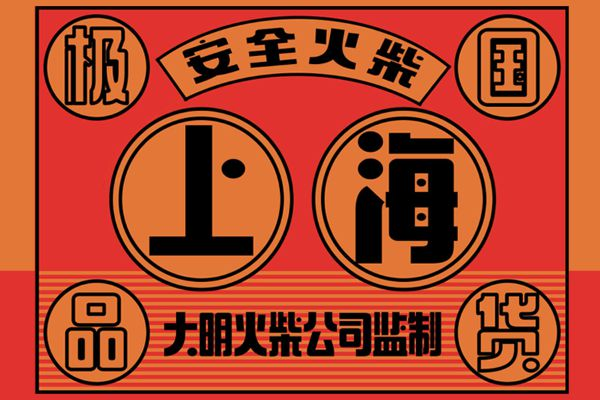
点字明刻本婉宋
点字明刻本婉宋是一款带有宋体韵味的字体,但比传统宋体多了一份婉约和柔和。适合传统风格的邀请函,尤其是中式婚礼、传统节日活动等。既有宋体的优雅,又不失温婉的气质。
江西拙楷
江西拙楷是一款带着朴拙手工感的楷书。和传统的楷书不太一样,它不是那种规规矩矩的写法,而是保留了手写的质朴感。适合中式婚礼请柬,或者带有传统文化元素的活动邀请。用在“囍”字、新人姓名和古风邀请语上,东方韵味很足。
字由锦绣
字由锦绣是一款中国风手写体,设计理念是“繁花如锦,神采挥洒”。方头起笔利落干脆,传递出力量感。适合国风主题的邀请函,比如中式婚礼、汉服活动、传统文化类聚会。兼具力量感与手写温度,用在标题上很有冲击力。
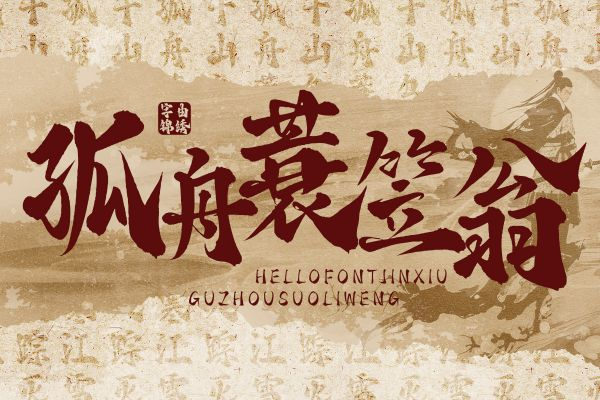
商务活动邀请函
字由文艺黑是一款现代简约风格字体,字形方正饱满,重心居中。保留了黑体的稳重感,但又加入了艺术弧线的设计,不会显得太死板。适合做邀请函的主标题或者新人名字的排版。不管是婚礼邀请还是活动邀请,用这个字体做标题都很提气。
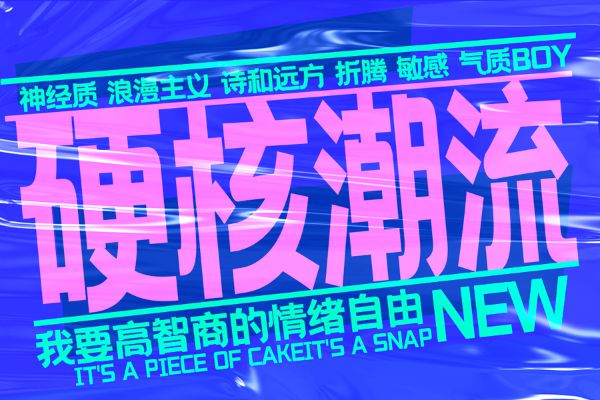
字由长宋
字由长宋传统宋体的装饰性元素做了简化和几何化处理。瘦长的结构,冷静清晰。适合简约、精致、当代感的邀请函。我做过一次设计展的邀请,用这个字体做正文排版,干净利落,阅读体验很好。
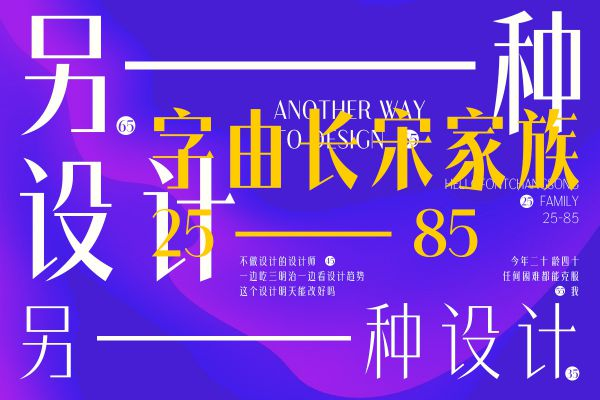
思源宋体
谷歌与Adobe联合打造的开源现代宋体,端庄优雅。字形方正稳重,保留了宋体的传统韵味,又融入了现代设计感。如果邀请函信息比较多,用思源宋体做正文,清晰又体面。
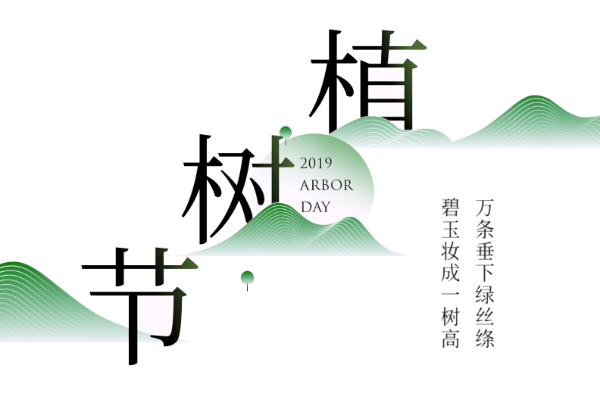
优设标题黑
优设标题黑方正有力,笔画粗重有设计感。属于展示类黑体,视觉冲击力强。适合做时间、地点的标注,或者邀请函中需要突出的关键信息。我经常用它来标日期和场地,粗重有力,一眼就能看到。
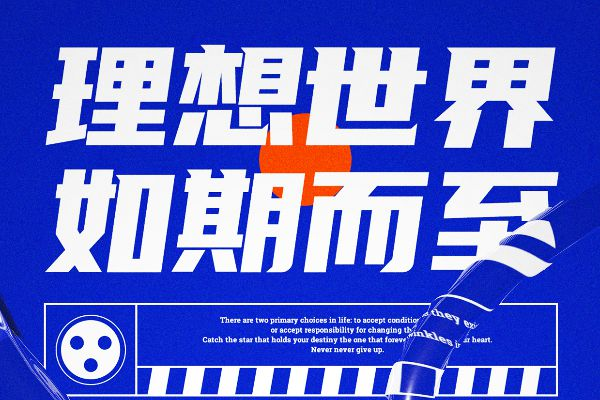
文艺/创意活动邀请函
剑豪体
剑豪体是Aa字库推出的中国风手写体。中宫收紧,结构紧凑中透出张力。笔型融入利落斜切,有剑势般的刚劲。适合武侠风、古风类的邀请函。江湖气息很浓,用在武侠主题的活动上特别对味。
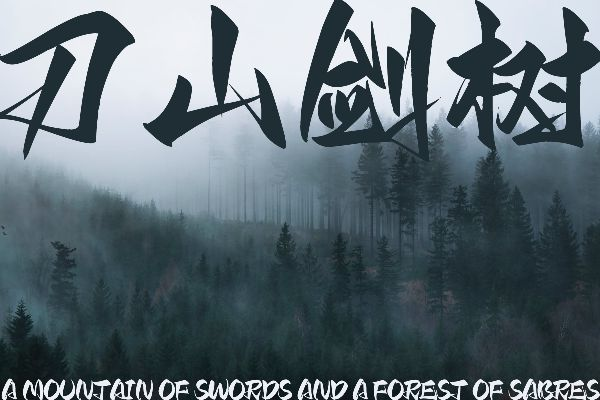
字由拂尘
字由拂尘字内重心上移,中宫收紧,有一种飘然入云的感觉。笔画中融入了篆书的写法,古意盎然。适合追求禅意、雅致风格的邀请函。书法展、茶会、雅集这类活动的邀请,用这个字体很加分。
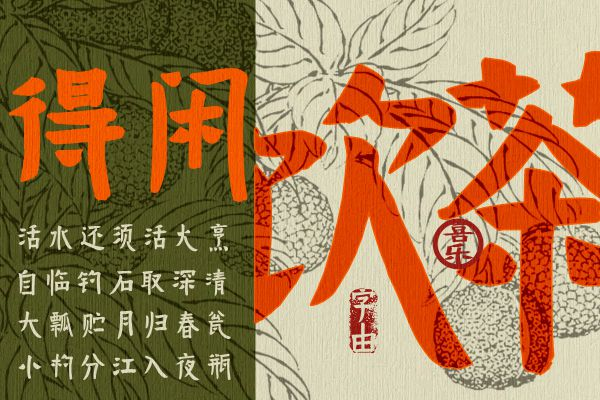
字由转转
字由转转是一款充满个性和文艺气息的手写体,线条流畅,笔画清晰。勾线装饰让字体多了一份灵动和活力。适合文艺风格的活动邀请,比如读书会、艺术展览、小众音乐会等。字体本身就带着一种“不随大流”的气质。